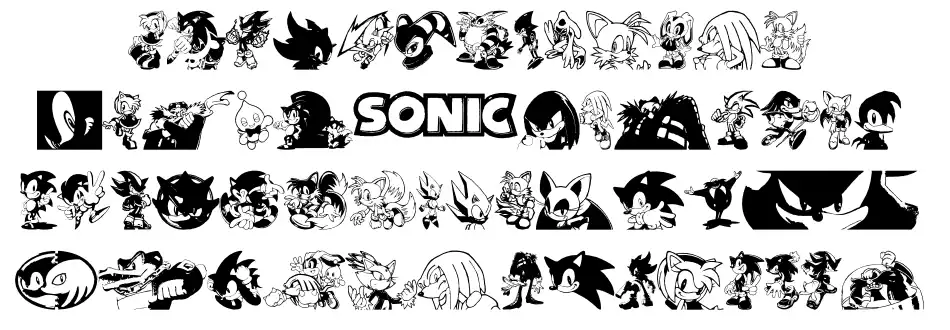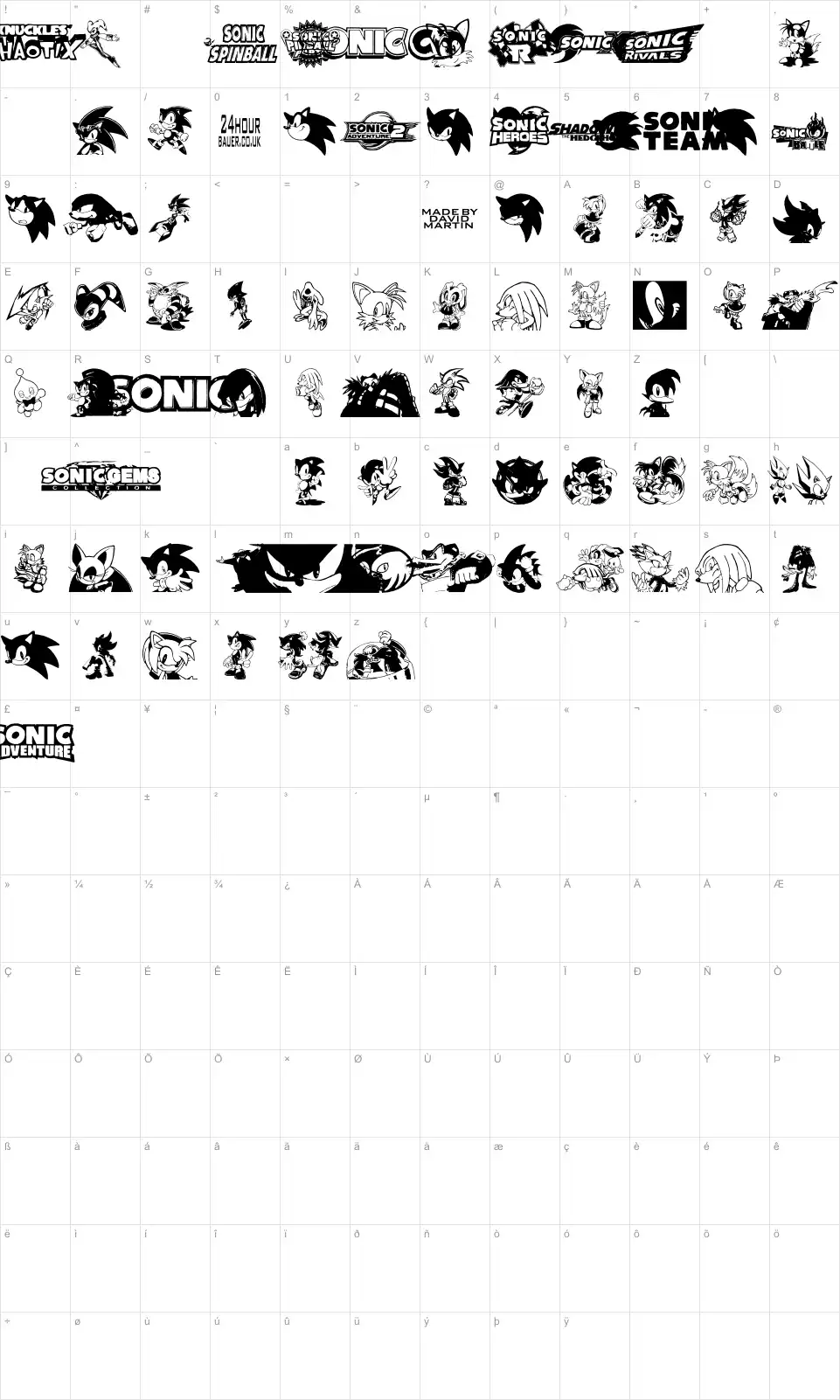
Sonic Mega Font – Download Grátis
A fonte Sonic Mega Font, criada por www.davidpustansky.com, é uma escolha ótima para designers que buscam uma fonte de jogo com um charme único. Adicionada à coleção de Dingbats no final de 2022, essa fonte é ideal para aplicativos como jogos ou interfaces de mídia interativa. Com licença gratuita para uso pessoal e um formato TTF, Sonic Mega Font oferece uma variedade de símbolos e gráficos que podem ajudar a personalizar e dar vida à sua obra. Se você está procurando por uma fonte visualmente atraente e versátil, Sonic Mega Font certamente se encaixa perfeitamente no seu projeto. Com mais de 14.625 downloads e um tamanho de arquivo de apenas 230 KB, é uma opção versátil que se adequa a uma variedade de projetos. Acesse www.davidpustansky.com para mais informações sobre outras fontes de sua autoria.